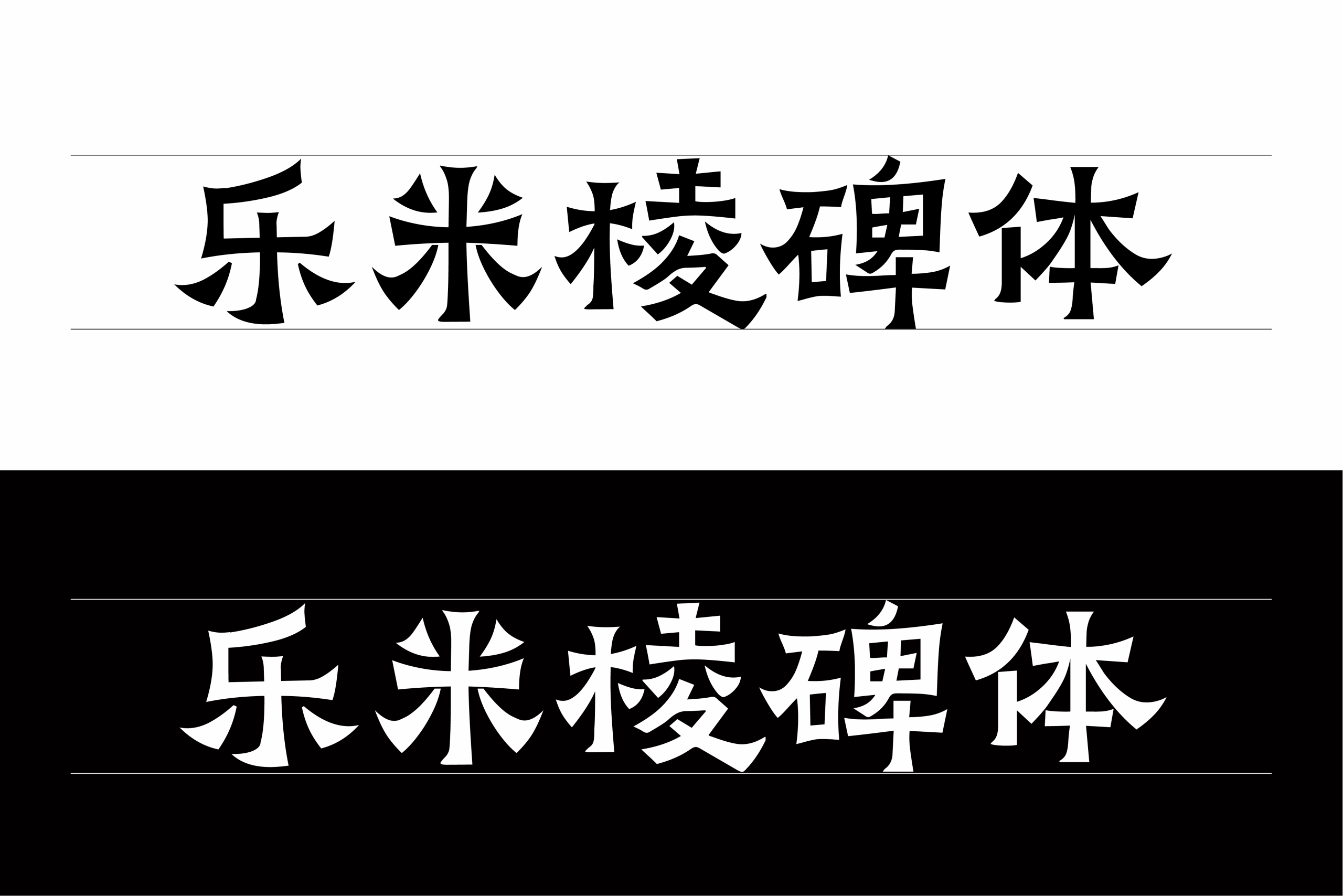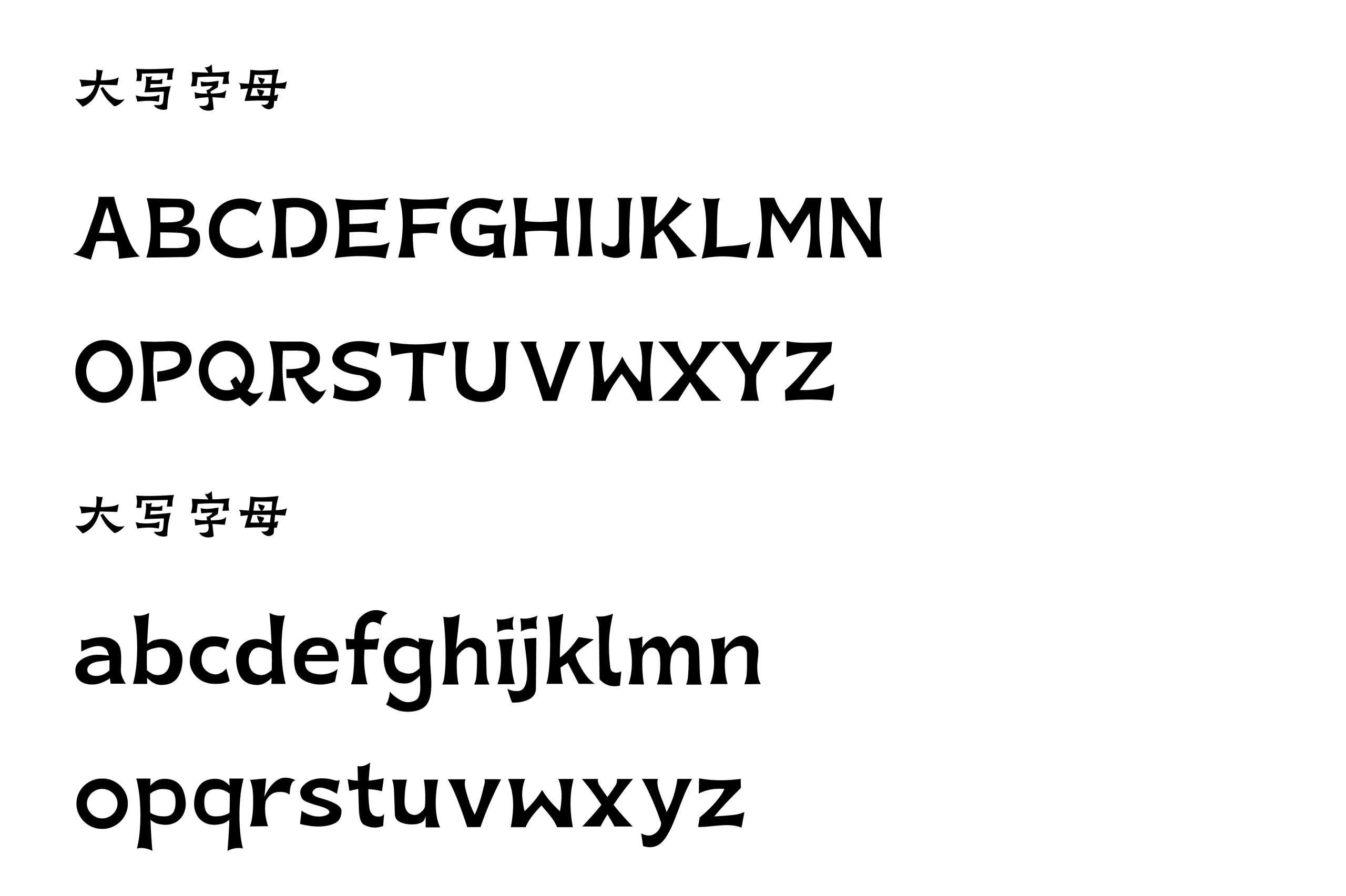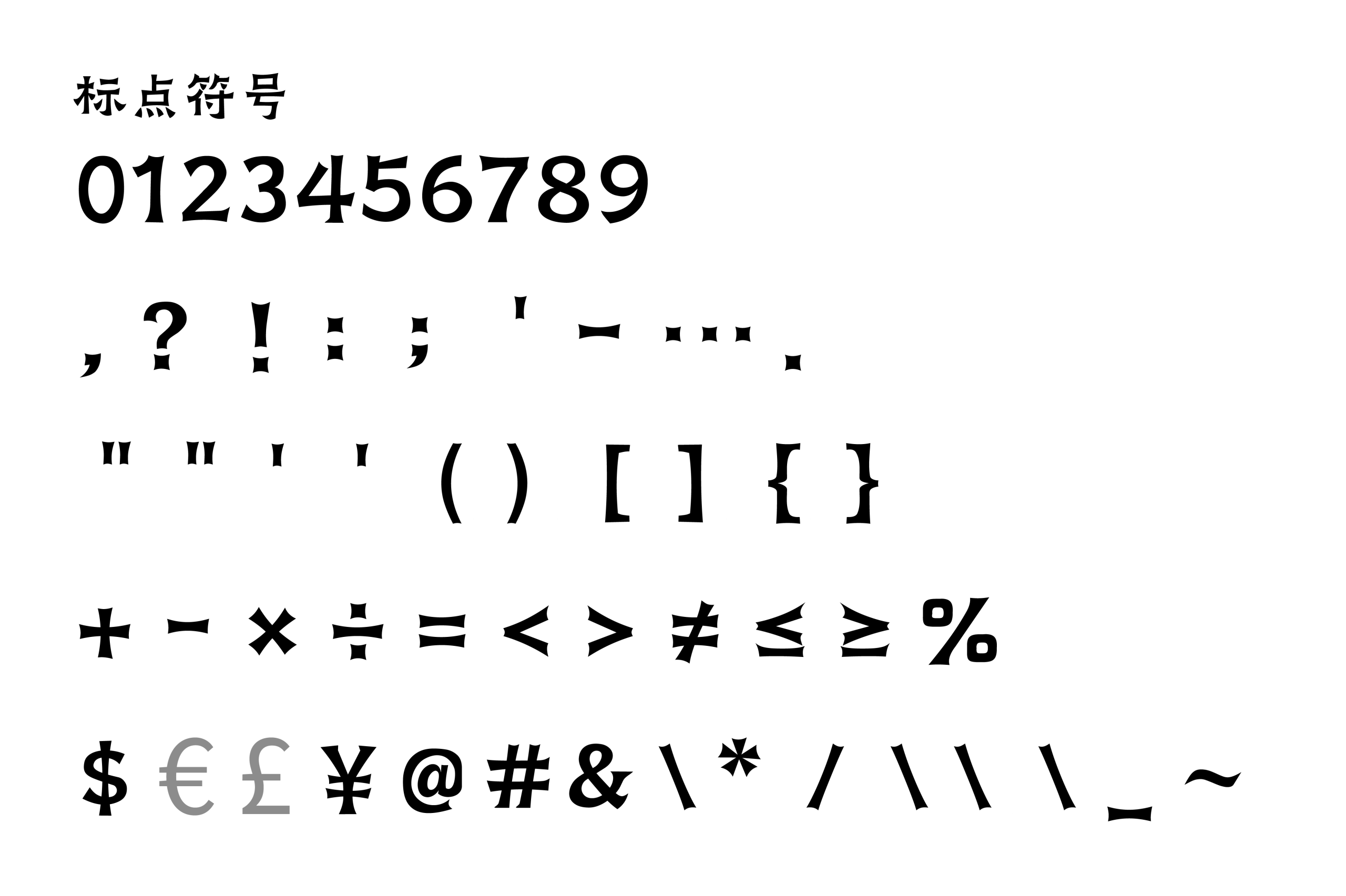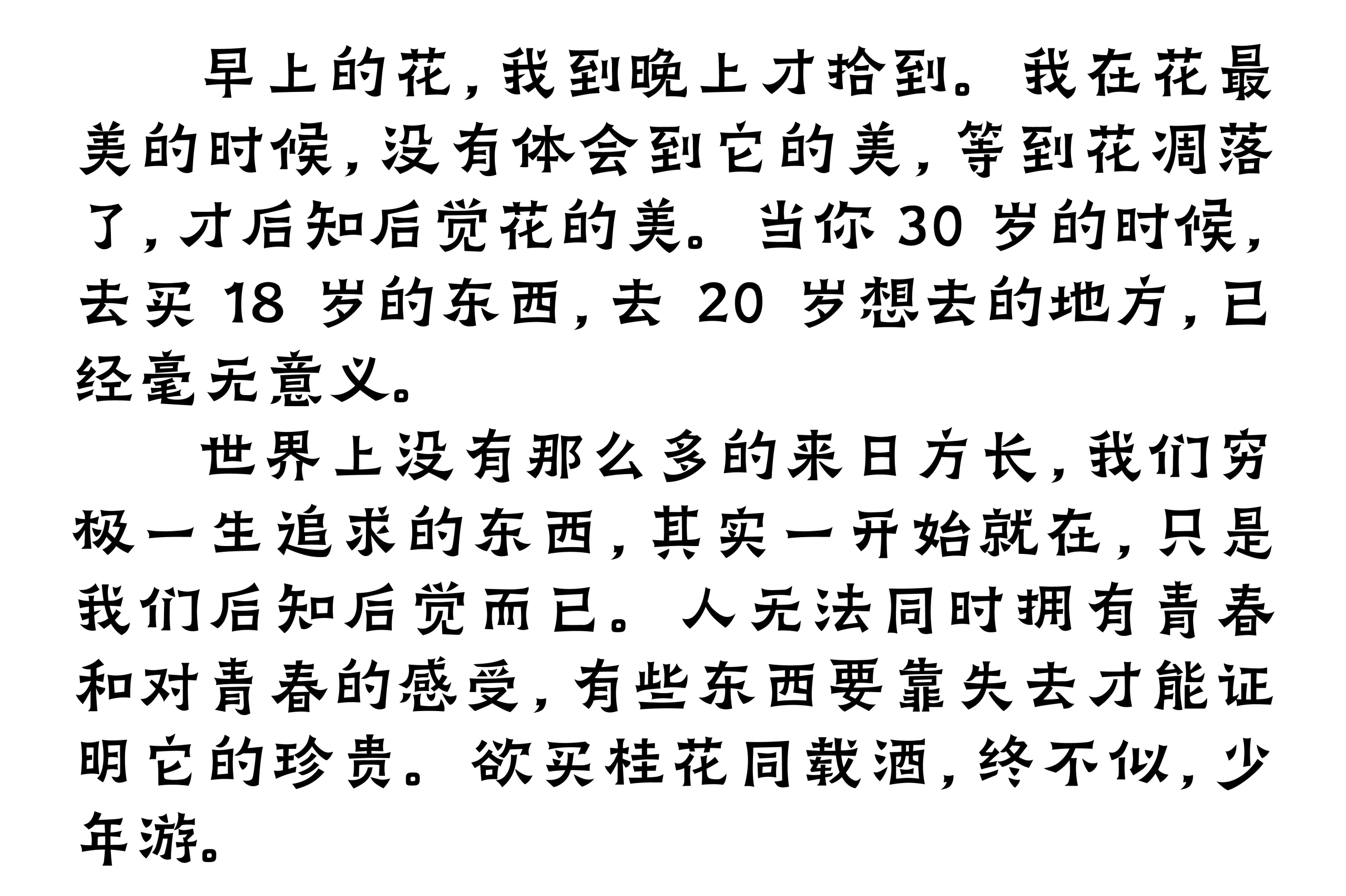
乐米棱碑体
乐米棱碑体是一款由杭州乐米网络科技有限公司发布,并提供免费商用授权的中文字体。字体以独特的棱角笔画和鲜明的结构变化为主要设计特征,在汉字原有结构的基础上融入更加大胆的视觉处理,让文字呈现出利落、硬朗而富有张力的整体气质。不同于常规中文字体对于规整与均衡的强调,乐米棱碑体更注重笔画之间的力量关系,通过富有变化的起收、转折与穿插,使每一个字都具有较强的造型感和辨识度。
从字形细节来看,乐米棱碑体的笔画具有较为明显的棱角特征,横竖之间的粗细变化以及撇捺的舒展收放形成了鲜明的视觉节奏。部分笔画在起笔和收笔处采用较为锐利的处理,使文字轮廓呈现出类似切削般的力量感;而部分转折则通过夸张的形态变化强化字形的视觉重心,让字体在保持汉字基本识别性的同时,又拥有更加鲜明的个性。整体字面结构舒展而不失厚重,笔画之间形成疏密有致的空间关系,在大字号使用时尤其能够展现字体本身的造型魅力。
乐米棱碑体并不局限于中文字符,其英文字母、数字及标点符号同样延续了整体的设计语言。英文字母在结构上融入了具有棱角感的笔画特征,大小写字母均保持较强的视觉个性;数字与常用符号则通过相似的笔画逻辑进行设计,使中文、英文、数字混排时能够形成统一的视觉风格。这种完整的字符设计也让乐米棱碑体不仅适合单纯的中文标题,同时能够满足海报、品牌视觉以及宣传物料中的多语言排版需求。
在视觉气质上,乐米棱碑体兼具传统汉字的文化底蕴与现代设计的表现力。它没有刻意追求柔和或圆润的视觉效果,而是通过更为明确的棱角和笔画力量建立字体自身的性格,使文字在画面中具有较强的存在感。尤其当字体以较大的字号进行排列时,笔画之间的粗细变化和局部造型会更加突出,能够自然形成视觉焦点,因此非常适合作为需要强调个性与主题氛围的展示型字体使用。
在实际设计中,乐米棱碑体适用于海报标题、品牌宣传、文化活动、展览视觉、文创产品、包装设计以及新媒体封面等场景。对于国风、潮流、文化创意等具有较强视觉属性的设计主题,它能够通过独特的字形为画面增加力量感和辨识度;用于短句、主题名称或宣传语时,也能够让文字本身成为设计的一部分。相比将字体作为单纯的信息载体,乐米棱碑体更适合发挥其展示属性,通过字号、字距和排版方式的变化进一步强化整体视觉效果。可前往乐米字库官网免费申请:https://font.leminet.cn/#/